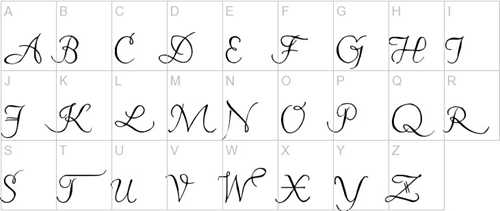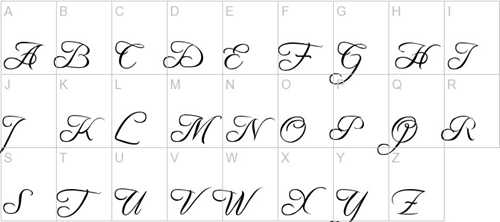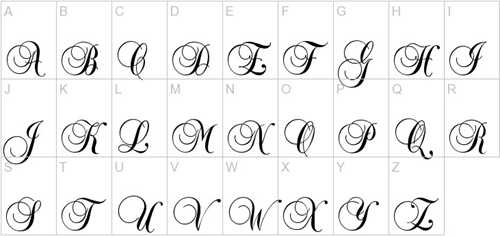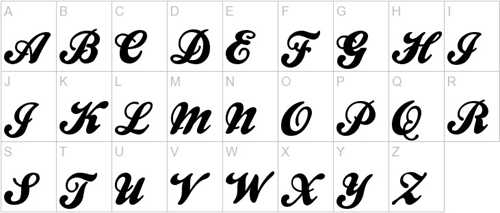
На этой странице красивые буквы для ников. Кириллические буквы русского алфавита и латинские.
Тут собраны красивые, интересные, необычные символы разных письменностей мира, похожие на буквы кириллицы и латиницы. Их можно использовать, когда нет возможности поменять шрифт, а разнообразить текст очень хочется. Например, при переписке в социальных сетях, или для ников. Вот символ Ϭ. Вроде, русская буква б, а на самом деле, она из коптского алфавита. Называется чима (Shima). Её использовали египтяне 15 веков назад. Возможно, совпадение и не случайно — и коптский и кириллица были созданы на основе греческого алфавита. Но в русском букв больше. Это потому, что звуков в языке было больше. Недостающие буквы Кирилл и Мефодий (создатели русской азбуки), наверно, просто придумали. Отсюда такие сложности с поиском аналогов для Я, Ю, Ы, Ъ. Если есть желание, можете сами просмотреть разделы, возможно, найдёте много интересного.
Кроме того, далеко не все символы Юникода поддерживаются шрифтами. В тексте, вместо них отображаются такие 𐇠𐇡𐇢𐇣𐇤 квадратики.
Многие из этих красивых букв (или просто странных) являются модификациями стандартных литер. Разные точки и штрихи — это диакритические знаки. Ими обозначают особенности произношения в разных языках, такие как долгий гласный звук или мягкая согласная. Забив в поиск на сайте какую-нибудь букву, можно узнать откуда она взялась. Для ников (и не только) можно (если можно) использовать также цифры и другие символы для ника из Юникода.